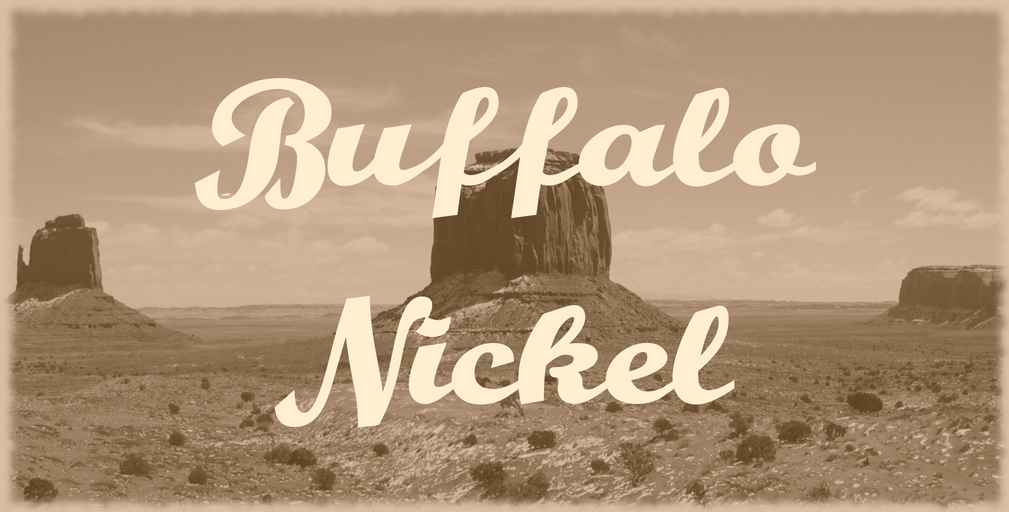
Esta fonte handwritten, batizada de Buffalo Nickel Font, é uma excelente escolha para aqueles que buscam adicionar um toque único a seus projetos digitais. Ela traz uma atmosfera envolvente e natural, perfeitamente adequada para aplicativos em categorias como design editorial ou publicidade. Além disso, esta fonte inclui elementos adicionais como sobrecargas de tração e bordas comestíveis que permitem criar banners, fazendo-a particularmente interessante para designers digitais que desejam dar um toque especial aos seus projetos. O designer Hamilton criou uma versão da Buffalo Nickel Font especialmente adaptada às necessidades dos times espirituosos, chamada Team Spirit NF. Esta versão incorpora sobrecargas e traços de bandeira em forma de swashes que promovem a união e espírito comunitário. A ideia é que esta fonte seja usada não apenas para estilizar o texto, mas também para celebrar a força da comunidade. Em um mundo digital cada vez mais interativo, uma boa fonte handwritten pode ser vital no seu projeto, oferecendo um toque pessoal e personalizado que ajuda a criar um impacto duradouro. Com Buffalo Nickel Font e seus adicionais de sobrecargas e swashes, você tem tudo o que precisa para estilizar textos de maneira única e elegante.